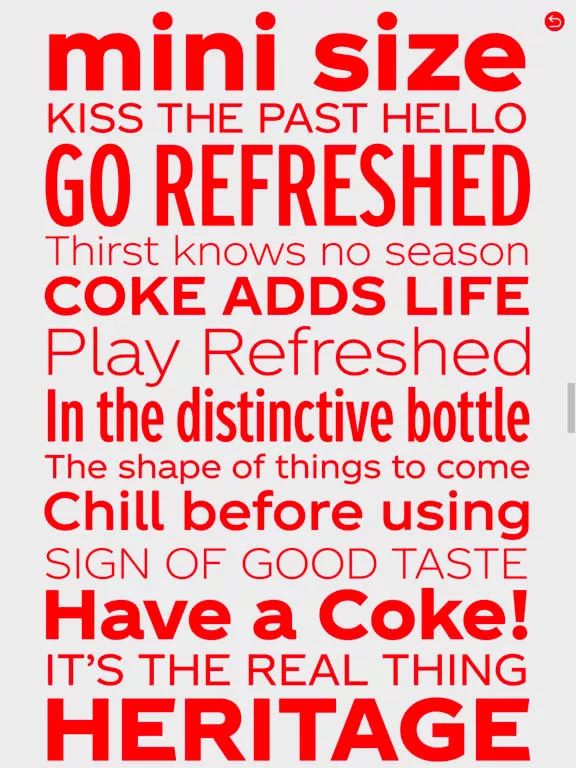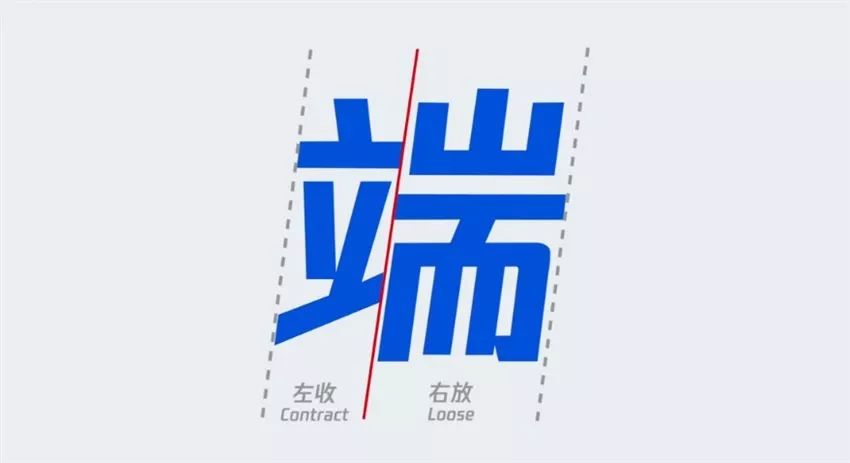
分享几个大公司/品牌的定制字体
最近,字体在设计中的功能不仅仅是表达信息这么简单了,有时候它更像是一款名片,承载了品牌价值。
让我们来看看为什么近年来越来越多耳熟能详的品牌抛弃了“Helvetica”,转而开始设计能传达他们自己品牌理念的字体呢?
随着时代的发展,曾经是世界上最受欢迎的字体——Helvetica 渐渐淡出了我们的视野,仿佛成为了过气网红。
尽管到2015年为止,Helvetica 作为互联网世界和设计界的宠儿,被广泛地应用。但是我们不得不接受这个不可逆转的趋势,自从iOS和Mac开始使用苹方,短短几年,Helvetica 的地位就开始动摇了。
对此,我们也必须承认,这款字体被广泛地应用在各个方面,非常百搭,但这意味着它没有什么特性,无法突出品牌的形象、价值。
大家想想啊,这些大公司每年花大把钱使用的字体,却在移动设备上显现不出优势,就理解为什么Helvetica 会“过气”了。
与其找相似的字体做替换,不如自己定制一套专属字体,这就是为什么最近定制字体的趋势越来越明显的原因。
下面我们就来欣赏一下几个大公司/品牌的定制字体吧!
Roboto
2011年为了适配安卓系统而生的Roboto发布了,而且是开源字体,一直以来受到许多公司的青睐。
San Francisco
因为在较小的屏幕上Helvetica 的显示并不是十分友好,随着apple watch的发布,苹果公司决定开发一套自己的专用字体——San Francisco。就是我们常说的苹方,也是一款开源字体。
IBM Plex
2017年末的时候,IBM也发布了自己的字体——IBM Plex,为公司省了不少购买Helvetica 使用权的费用。对于使用权方面,大公司也是非常豪爽的,IBM Plex发布当天也公开了下载地址。
CNN Sans
2016年CNN也发布了专属字体,可惜使用权没有开放给大家。
YouTube Sans
灵感来源于播放键的油管字体2017年面试,主要用于他们公司的物料制作、ppt演讲等场合。
TCCC Unity
对的,大家没看错,是真的可口可乐。2018年,可口可乐公司发布了它们的字体——TCCC Unity,全称“The Coca Cola Company”。
为什么Helvetica 过气了
这种定制专属字体的方法,现在已经不仅仅是一个趋势,还是一种重新定义品牌的方式。
Helvetica 仍然是一款”挺好“的字体,但是由于有将近半个世纪没有更新,所以局限性也随着时代发展而逐渐显露出来。
这除了促进谷歌和苹果都开发了自己的字体以外,IBM的例子也让我们看出,字体是一个展现品牌价值的有效途径。
想象一下,现在有多少公司想要在互联网上抓取用户,他们在网上做视频,发文章,让销售模式发生了变化。使用专属字体不仅能让他们的品牌价值提升,长期来看还能为公司节约成本。
这样的营销方式在十年前根本是想象不到的,每个品牌都渗透在日常生活当中——像是穿着“可口可乐红”T恤、用“苹方体”做设计,打开手机看到的是谷歌字体……
中文字体也玩重构
有人可能又要说了,小编又拿英文字体说事儿,好那小编就换个去年刷屏朋友圈的例子,腾讯字体。
对于腾讯发布的这款新字体,大部分人还是赞许的,不过也有少数人持有“不就倾斜了一点”的意见。小编觉得,这种看法其实不科学,就跟你辛苦设计了一张海报,老板却觉得你就花十分钟一样。
一款字体的诞生,都是经过字体设计师和客户沟通,分析特点,再根据需求来创作的。腾讯的新字体前后经过大约一年时间的推敲,并不是“稍微倾斜了一下”就可以概括的。
最后
虽然并不是每个品牌都能重新设计自己的专属字体,但是并不意味着我们必须使用像Helvetica 这样的默认字体。我们可以运用一些已有的字库,来重构出与自己品牌形象相符的字体。